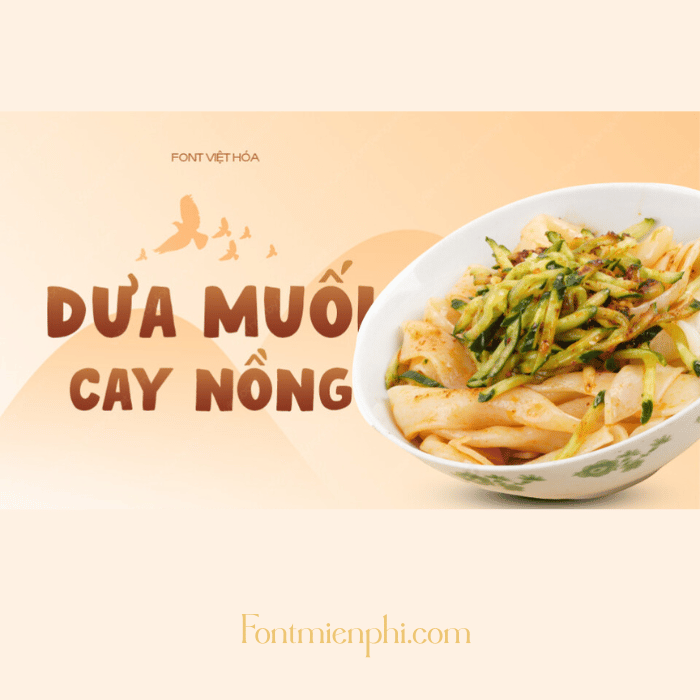
Font Việt hóa 1FTV VIP Moro Baby – Nét chữ đáng yêu, sáng tạo không giới hạn
Font 1FTV VIP Moro Baby là bộ font Việt hóa độc đáo với phong cách dễ thương, mềm mại, phù hợp cho thiết kế đồ họa, in ấn, giáo dục và sáng tạo nội dung. Với nét chữ tròn trịa, ngộ nghĩnh, Moro Baby giúp tạo điểm nhấn cho poster, thiệp mời, logo, hoặc các ấn phẩm dành cho trẻ em.
✔ Nét chữ mềm mại, đáng yêu – Phù hợp với dự án nhí nhảnh, trong sáng.